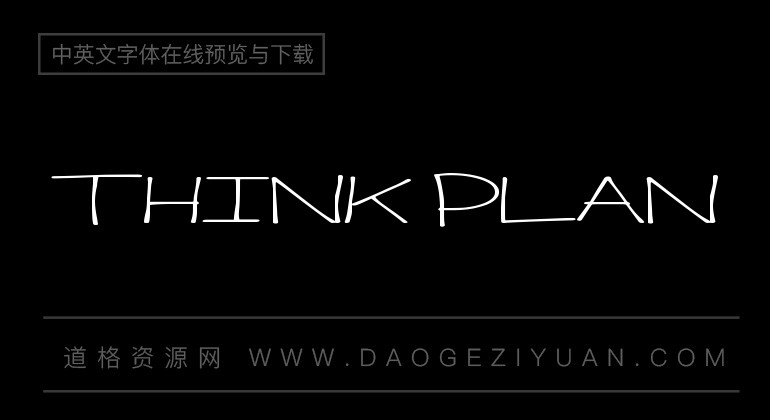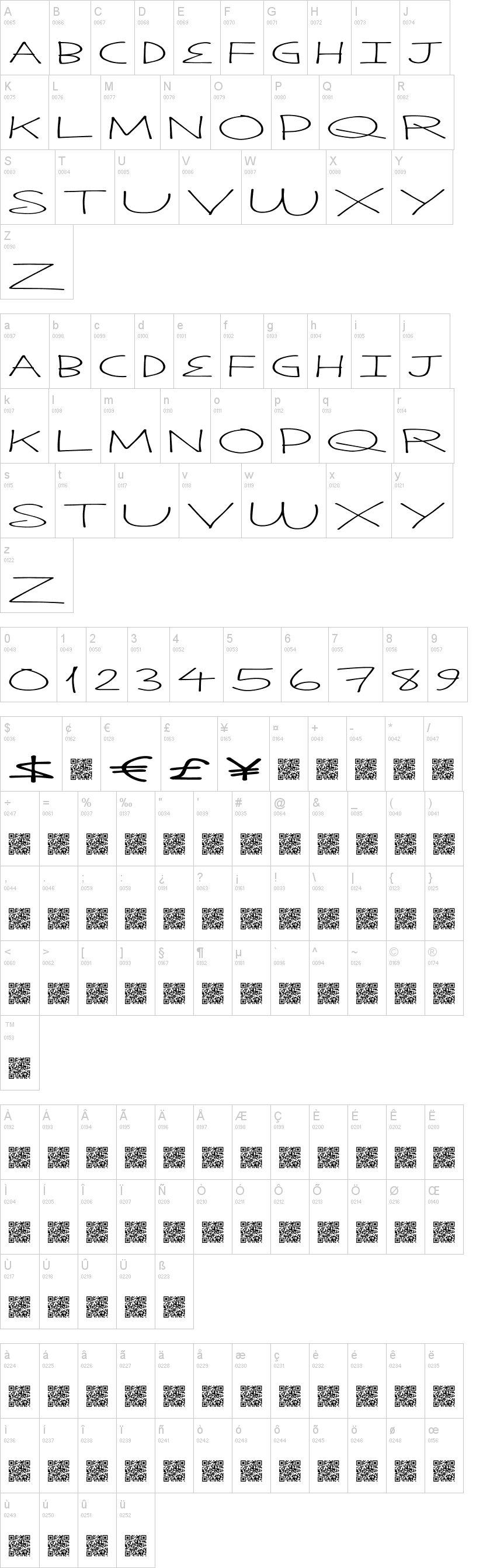
Think Plan
Think Plan 字体是一款清新优雅的手写字体,由 Think Plan 手写字体设计团队设计。它的字体风格灵感源自自然,拥有清晰的线条和柔和的曲线,给人一种自然、温暖的感觉。它的字体特点是细节丰富,字形清晰,而且能够支持多种语言,适用于多种用途,包括印刷、网页设计、报刊杂志、标志和品牌等。
Think Plan是一款非常不错的手写艺术字体,具有很好的视觉感,适合于文化类的宣传设计、商业类品牌的广告和产品包装设计以及个性化文字排版等较多场景。